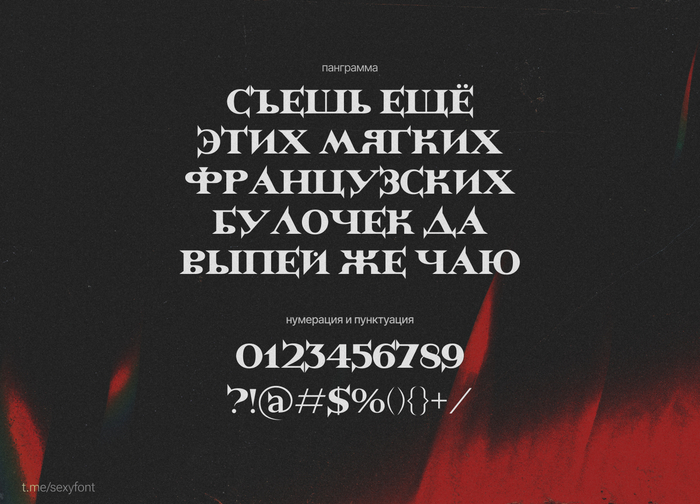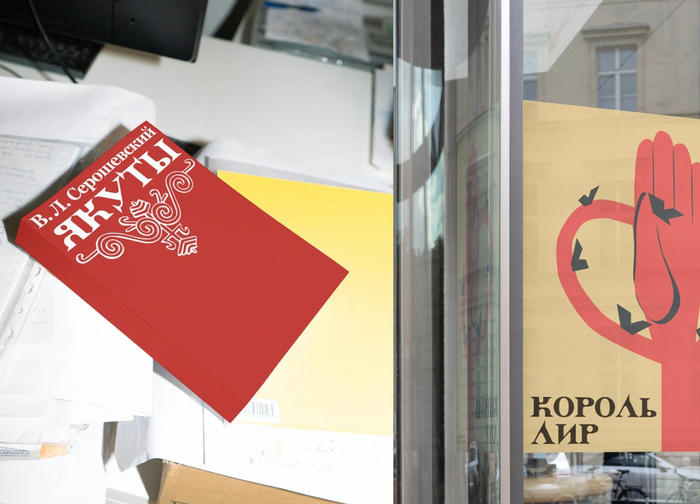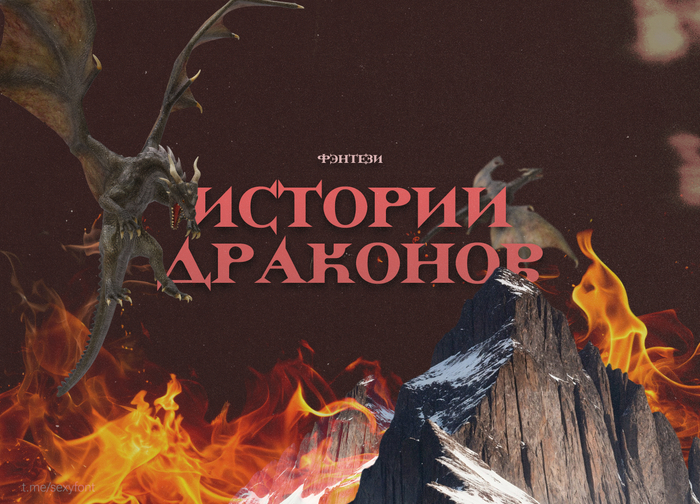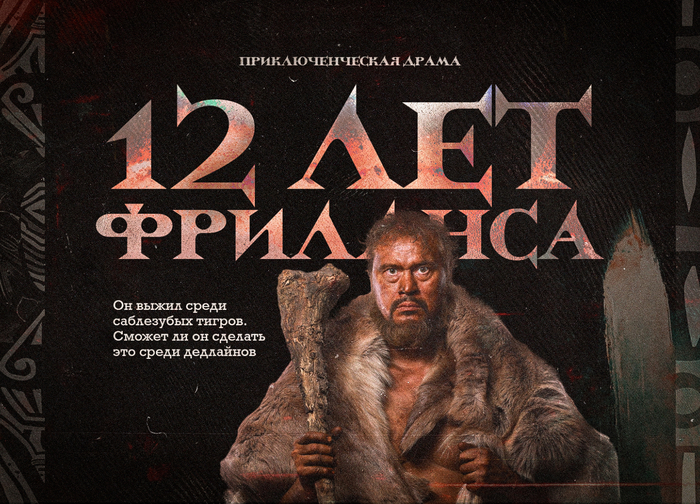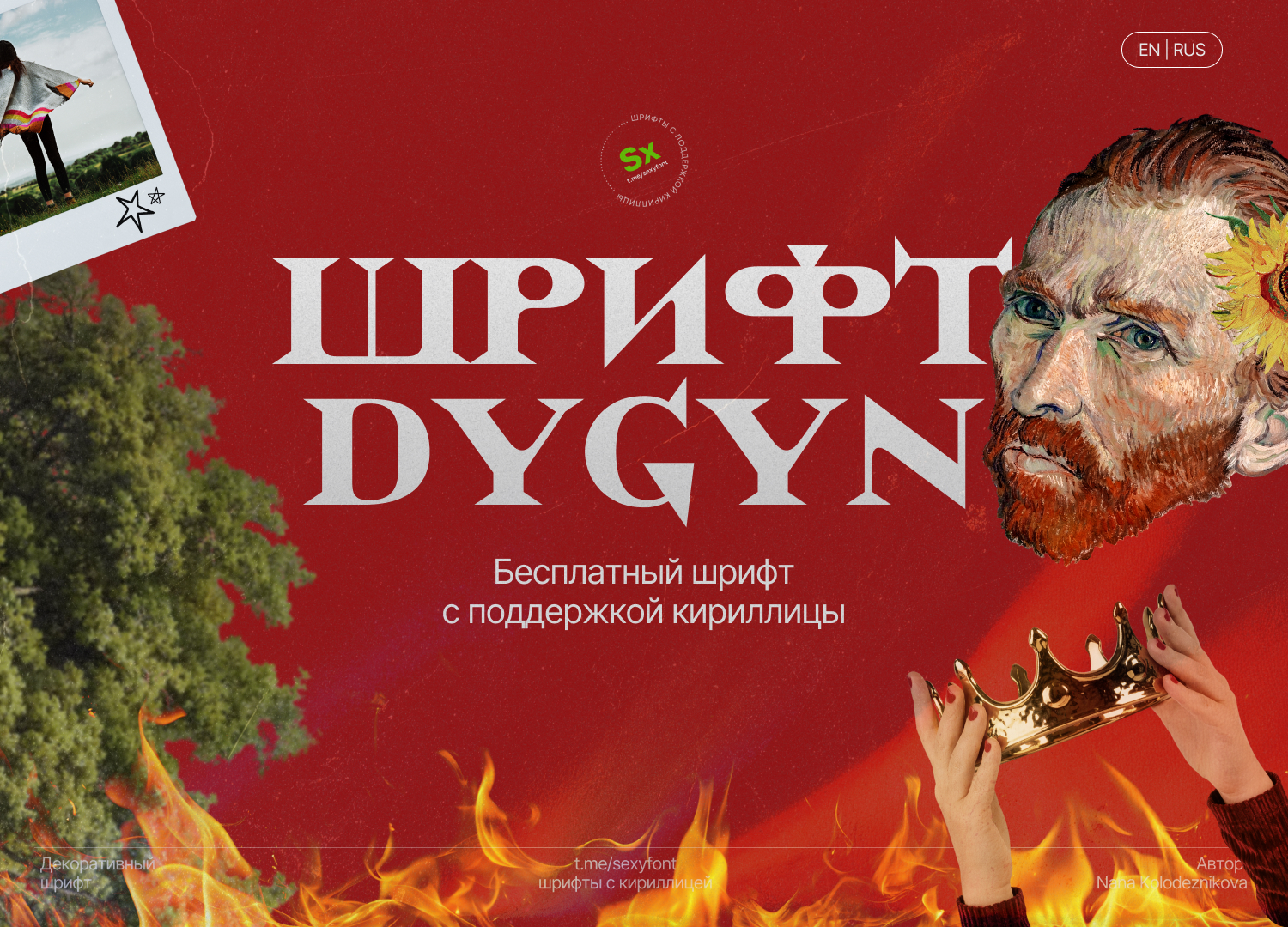
Бесплатный шрифт Dygyn
Дыгын - акидентная антика с северной душой. Шрифт, созданный на основе орнаментов народа саха.От автора: Шрифт, рождённый из орнаментов народа саха, веками передававшихся из уст в узор. В якутской мифологии слово «дыгын» означает «молния» символ мощи и стремительности, придающий слову особую энергию.Автор: Нана Колодезникова